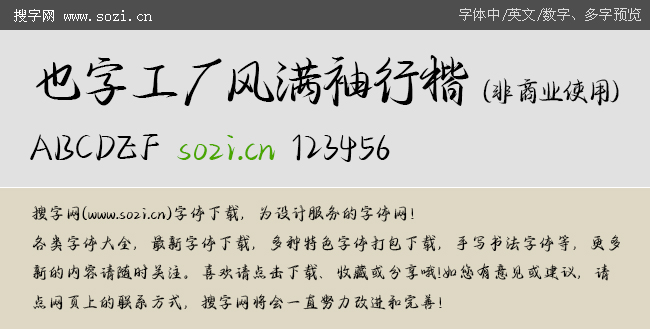
也字工廠風(fēng)滿袖行楷
搜字網(wǎng)給大家提供一款也字工廠風(fēng)滿袖行楷(非商業(yè)使用)中文字體下載,也字工廠風(fēng)滿袖行楷是一款手寫書法字體,字體書寫流暢自然,字形瀟灑大方。具有很好的視覺效果。適合應(yīng)用于藝術(shù)設(shè)計(jì)、平面宣傳設(shè)計(jì)、網(wǎng)頁設(shè)計(jì)、海報(bào)設(shè)計(jì)等應(yīng)用(此字體為個(gè)人非商用版,商用可以聯(lián)系:官方網(wǎng)址:https://yefont.com/home,聯(lián)系方式:13798980448)。